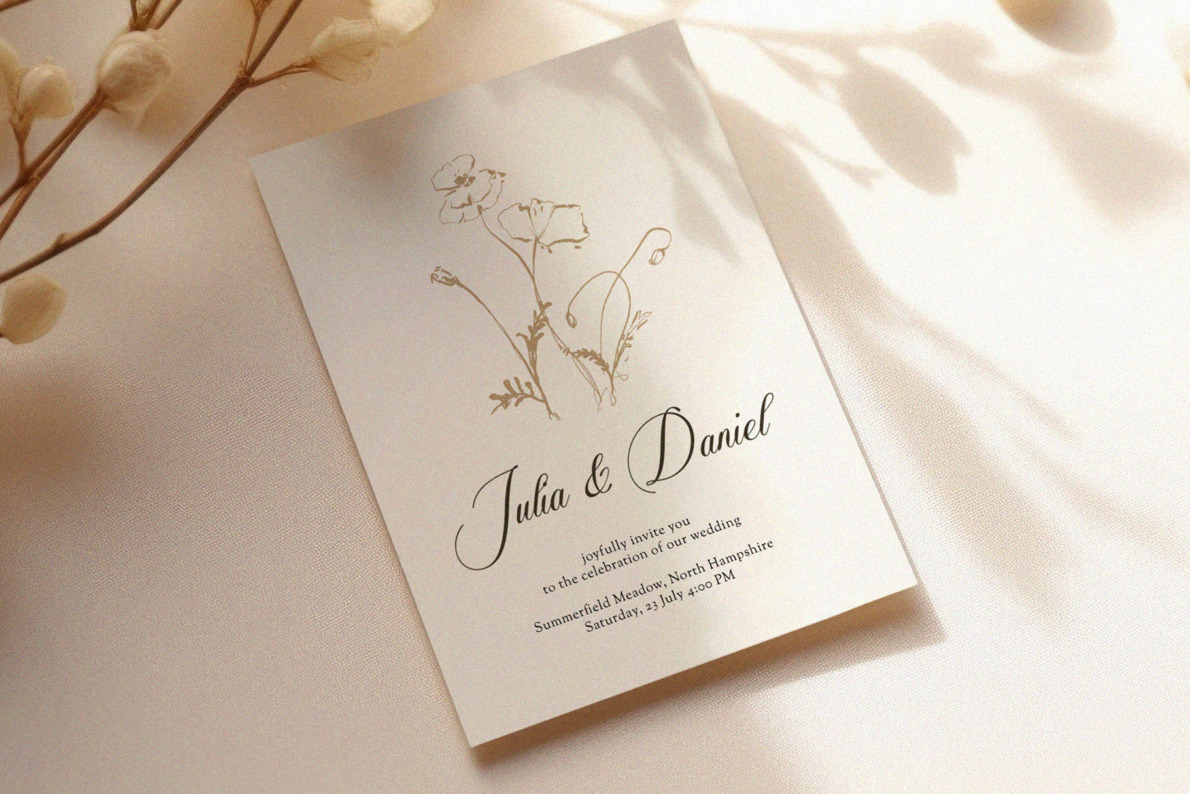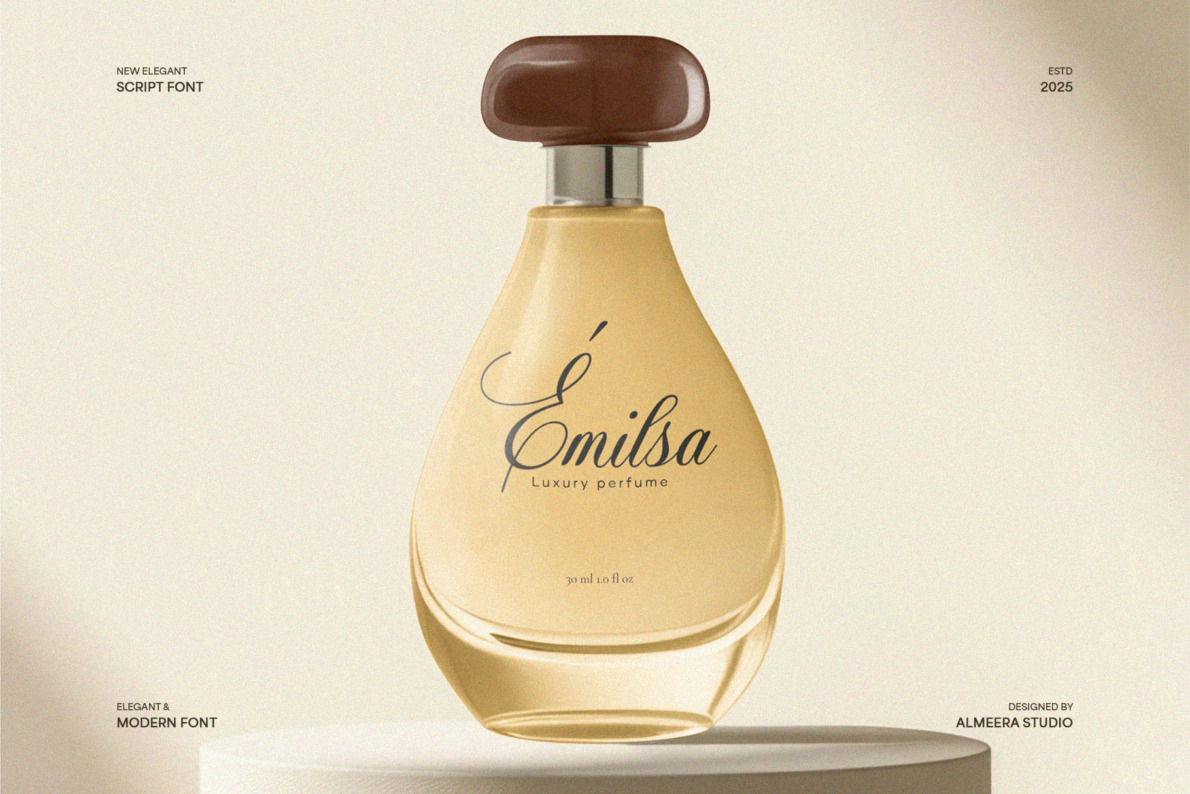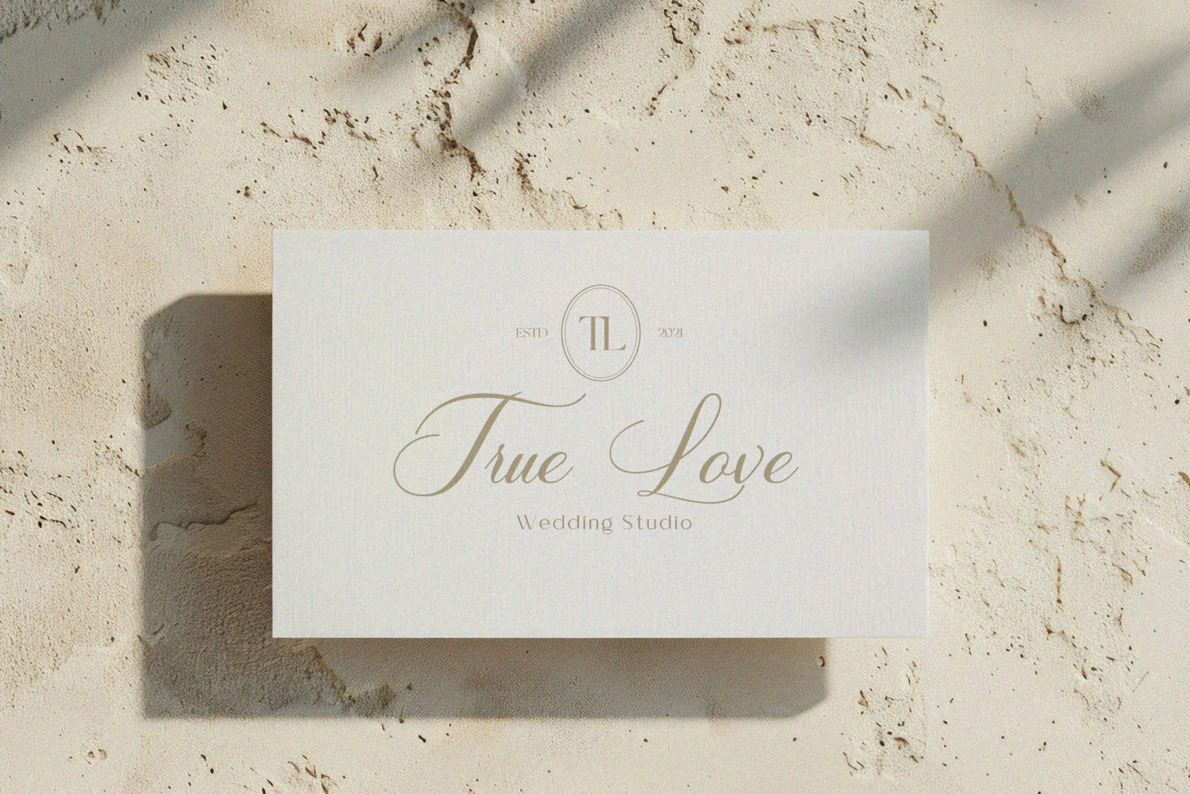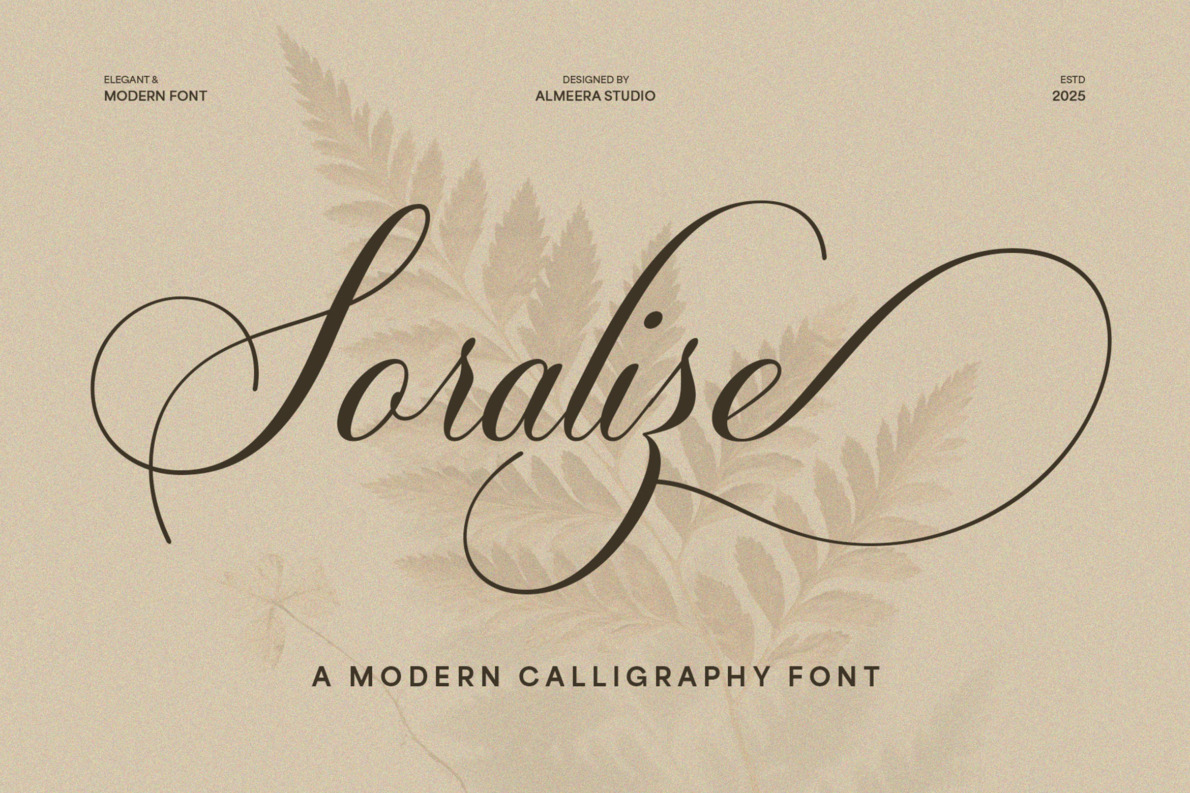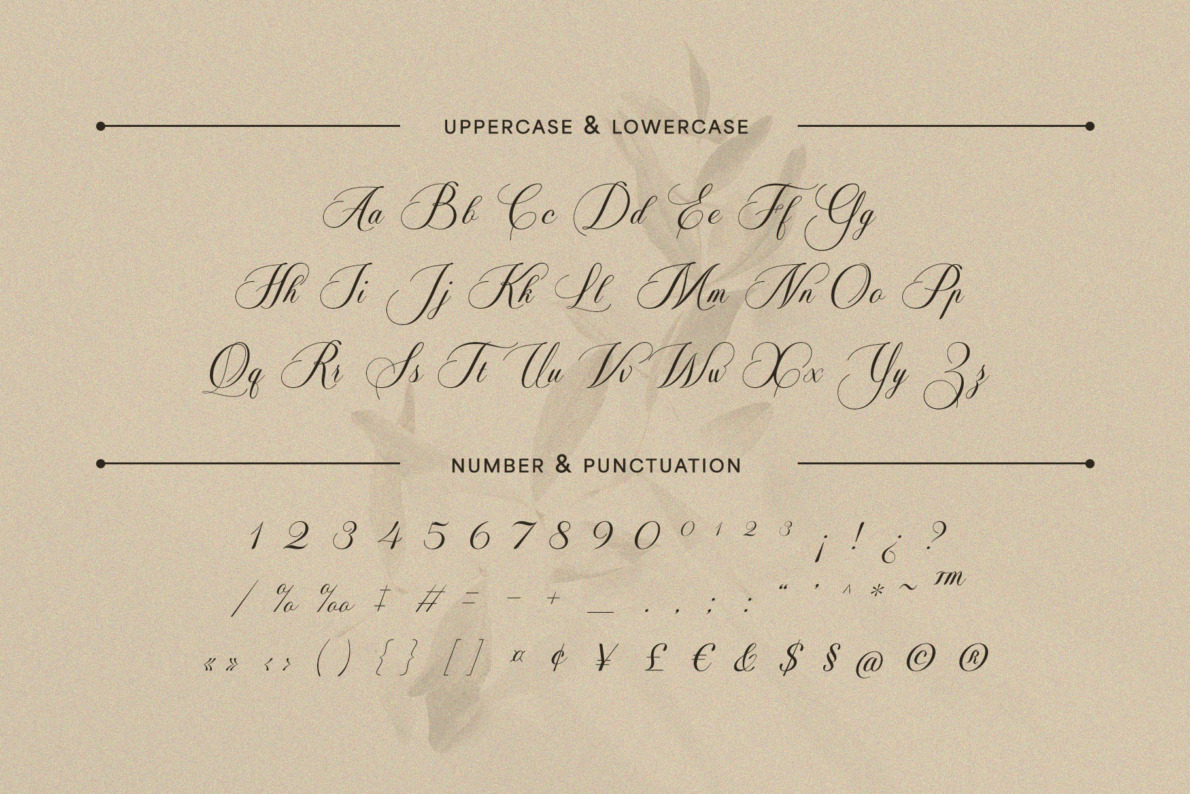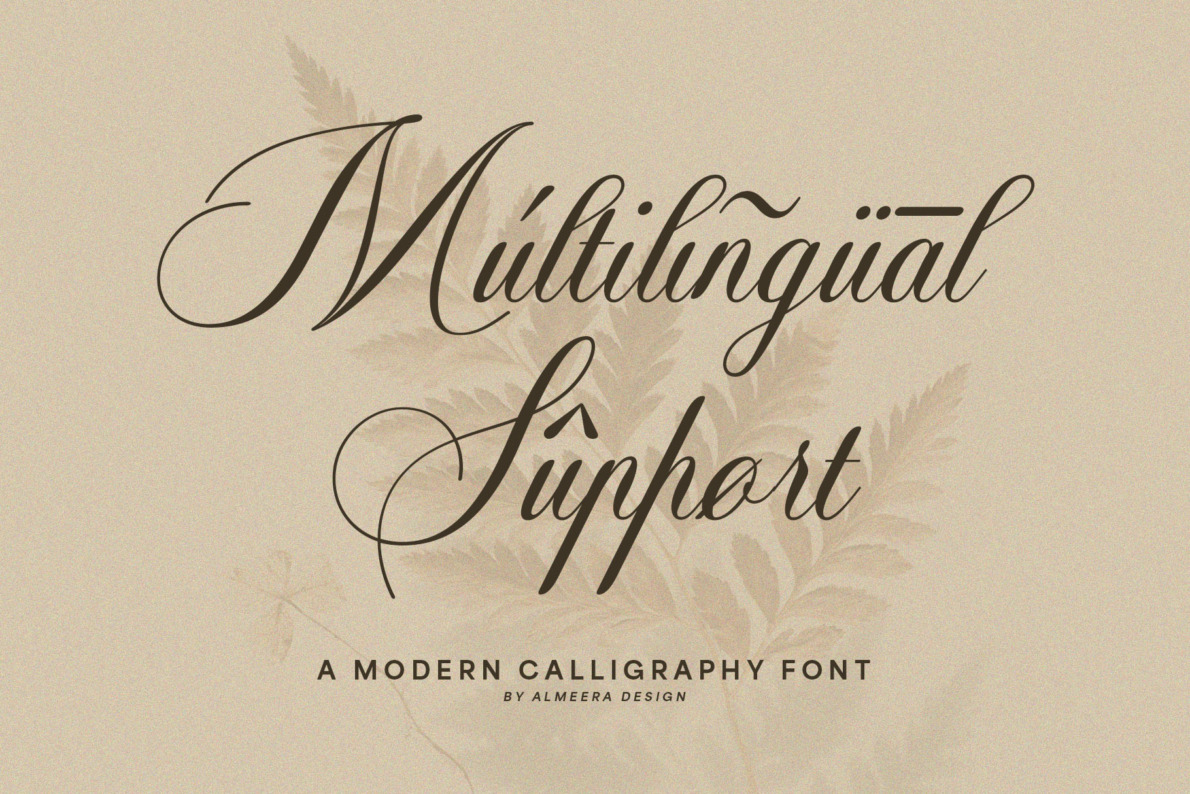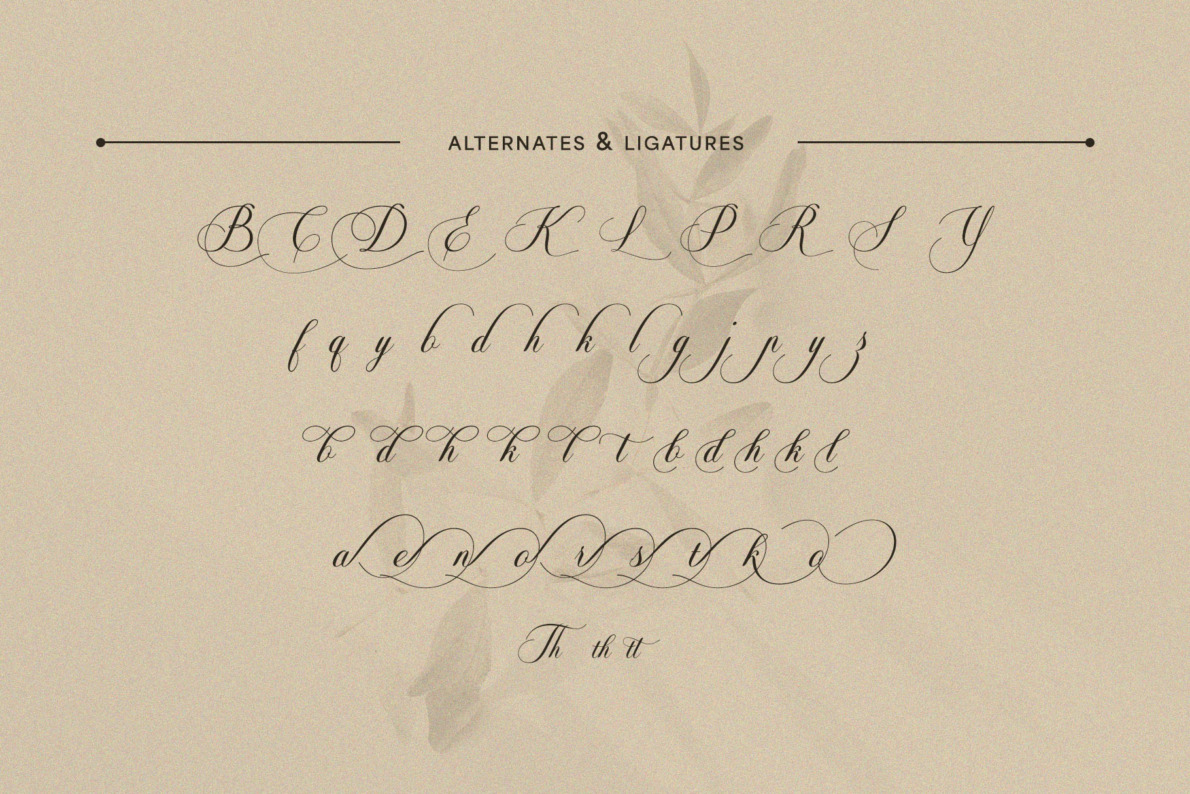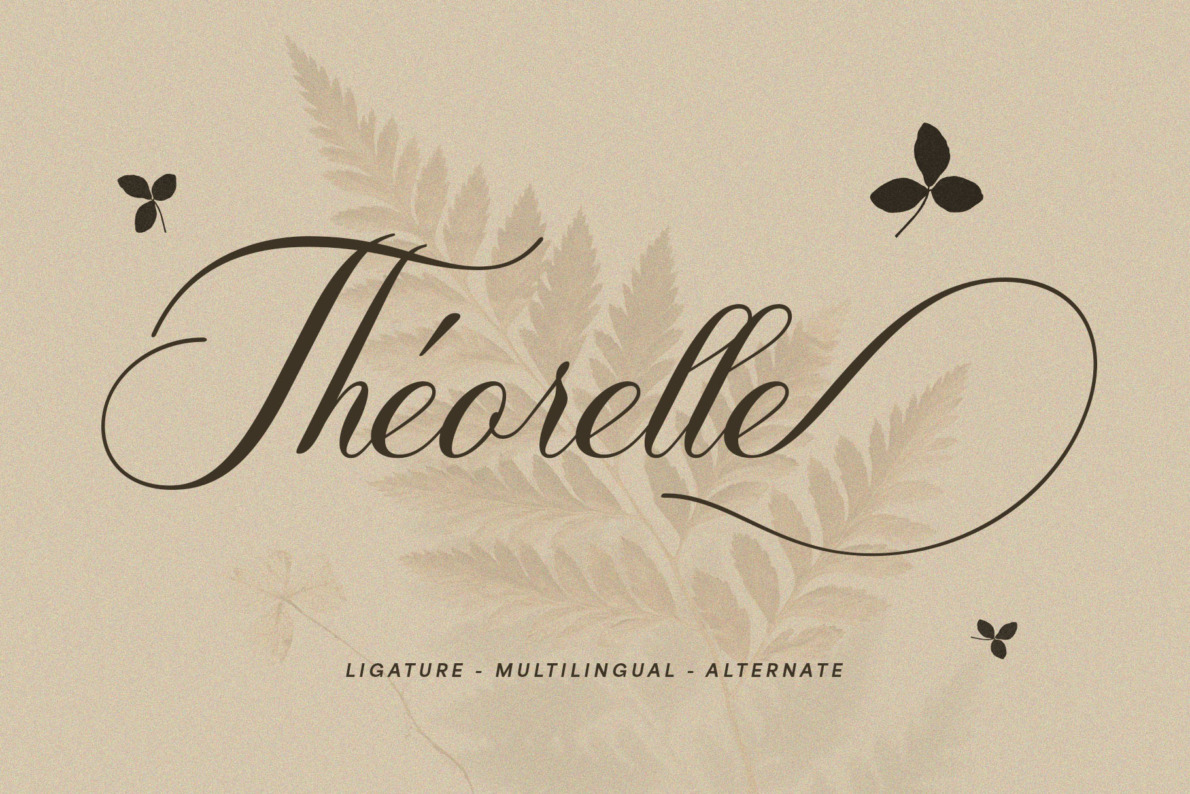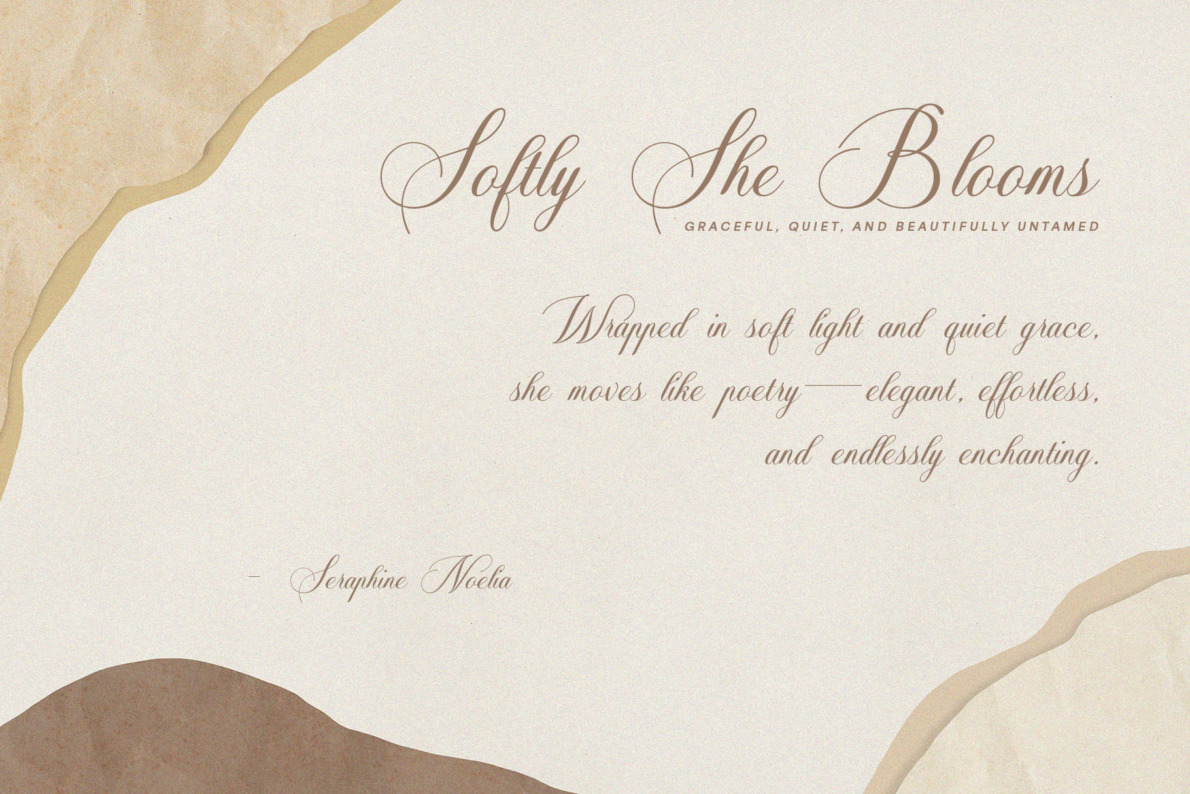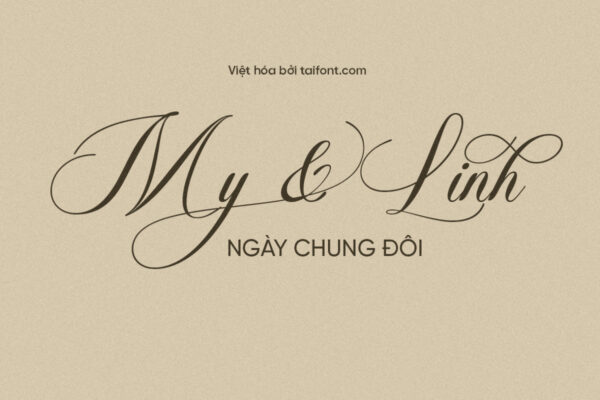
Giới thiệu về Font TF Soralize Việt hóa
TF Soralize Việt hóa là một font chữ viết tay (script font) nổi bật với vẻ đẹp tinh tế, lãng mạn và đầy duyên dáng, lý tưởng để tạo nên sự sang trọng và cá tính riêng cho các thiết kế. Font này mang đến cảm giác như một bức thư pháp được viết bằng tay một cách mềm mại và uyển chuyển, toát lên sự nghệ thuật và đẳng cấp. Điểm đặc biệt của Soralize là sự phong phú của các glyphs (ký tự đặc biệt) đẹp mắt, giúp tăng thêm tính nghệ thuật và sự độc đáo cho thiết kế.
Với sự tinh xảo trong từng ký tự, nét viết tay mềm mại và khả năng biến hóa qua các glyphs, Soralize là lựa chọn hoàn hảo cho các ấn phẩm cần sự sang trọng và khác biệt:
- Thiết kế thiệp cưới: Hoàn hảo để viết tên cô dâu chú rể, lời mời cưới, hoặc các thông tin chi tiết trên thiệp cưới, menu tiệc, bảng tên khách mời. Những nét chữ mềm mại, uyển chuyển cùng các glyphs độc đáo sẽ biến mỗi tấm thiệp thành một tác phẩm nghệ thuật, mang đậm dấu ấn cá nhân và sự lãng mạn của ngày trọng đại, đồng thời truyền tải sự ấm áp và trang trọng.
- Thiết kế thiệp mời: Lý tưởng để viết lời mời trang trọng cho các sự kiện đặc biệt, tiệc tùng, khai trương hoặc các buổi lễ. Font này sẽ làm cho mỗi tấm thiệp trở nên độc đáo, cao cấp và đầy thu hút.
- Thiết kế kỷ niệm và sự kiện lãng mạn: Phù hợp cho thiệp mời kỷ niệm ngày cưới, sinh nhật, hoặc các sự kiện cá nhân đòi hỏi sự tinh tế và cảm xúc.
- Thiết kế thương hiệu cao cấp (nhấn nhá): Có thể được sử dụng cho các chi tiết nhỏ trong logo, slogan, hoặc các ấn phẩm truyền thông của các thương hiệu muốn truyền tải sự sang trọng, tinh tế và thủ công.
Với TF Soralize Việt hóa, bạn có thể dễ dàng thổi hồn lãng mạn, sự tinh tế và vẻ đẹp vượt thời gian vào các thiết kế, tạo ra những sản phẩm không chỉ đẹp mắt mà còn đầy cảm xúc và sức hút đặc biệt.
Font Việt hóa TF Soralize – Font thiệp cưới nhiều glyphs